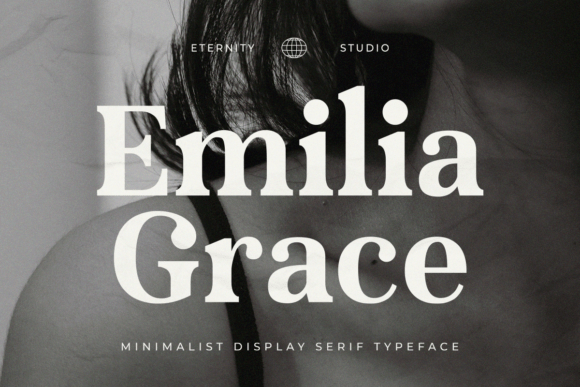
Et Emilia Grace
Jika anda sedang mencari aset berkualiti tinggi seperti Et Emilia Grace, pakej premium ini merupakan pilihan yang hebat untuk projek kreatif anda.
Dicipta dengan ketepatan, Et Emilia Grace menyediakan vektor yang bersih, tipografi yang licin dan lesen komersial untuk ketenangan fikiran.
Sama ada anda mencipta produk POD (Print on Demand), jemputan perkahwinan atau grafik media sosial, Et Emilia Grace amat bersesuaian.